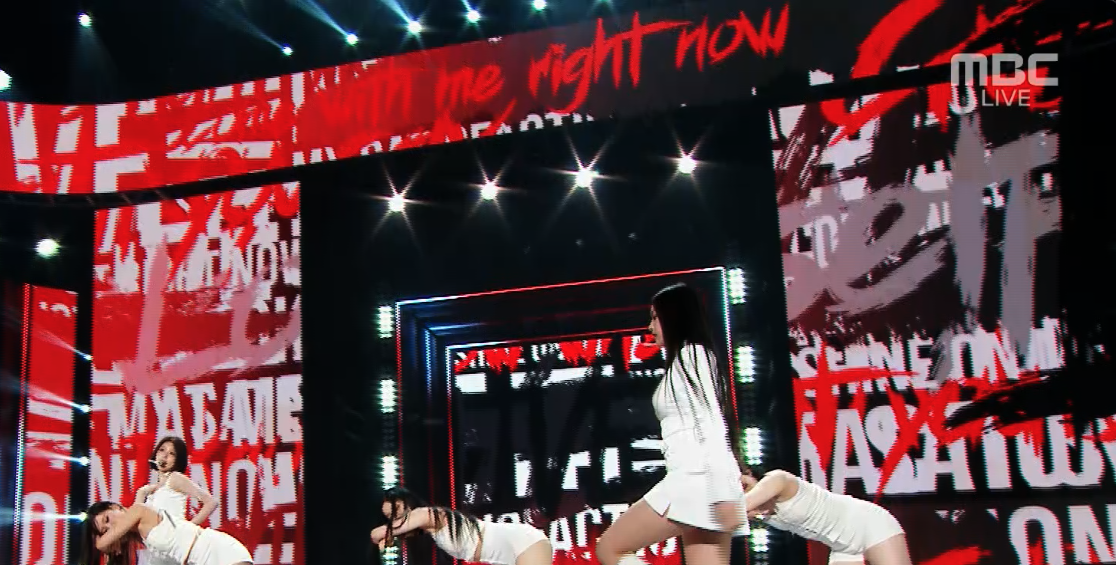
거친 낙서 폰트... kmy*** 2023.03.11 이폰트는 무슨 폰트일까요 거친 낙서한듯한 폰트 입니다 해외 폰트찾아주는 사이트에서 검색을해보아도 나오지 않아서 문의드립니다 댓글 0 등록 쉽고 빠르게 가장 비슷한 폰트를 알고 싶다면? 이미지로 검색하기
거친 낙서한듯한 폰트 입니다
해외 폰트찾아주는 사이트에서 검색을해보아도 나오지 않아서 문의드립니다